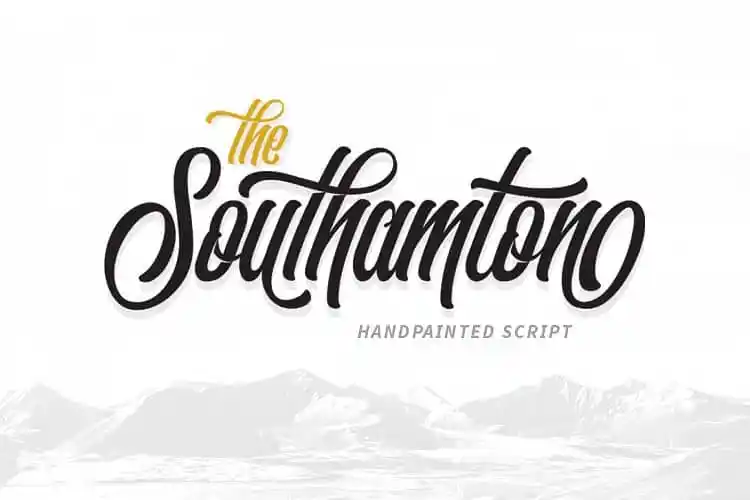
The Southamton Typeface – Download Grátis
Introduzimos The Southamton Typeface! Desenvolvido pelo designer 178-MC, este é um tipo premium disponível para download gratuito hoje na CreativeMarket. O The Southamton é uma tipografia pintada à mão com estilo personalizável, perfeito para aplicativos vintage e caros, logotipos, cartazes, materiais de propaganda e outros formatos. Suas linhas delicadas e traços distintivos permitem que você personalize a aparência conforme necessário. Aproveite esse tipo gratuito enquanto ele durar, é uma excelente fonte para projetos que valorizam o estilo retrô ou elementos artesanais em design gráfico.